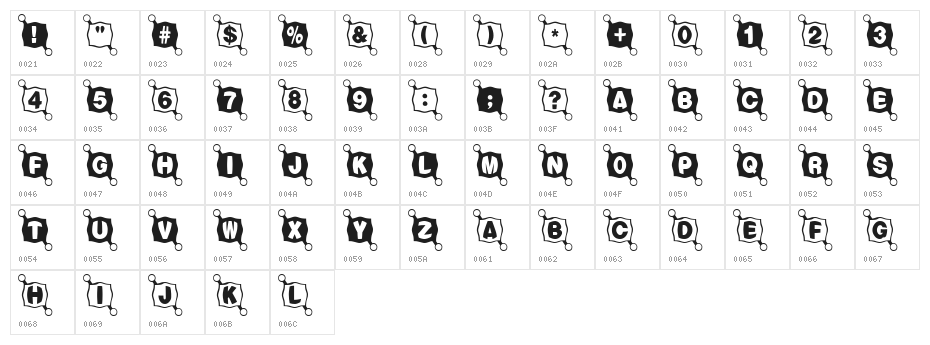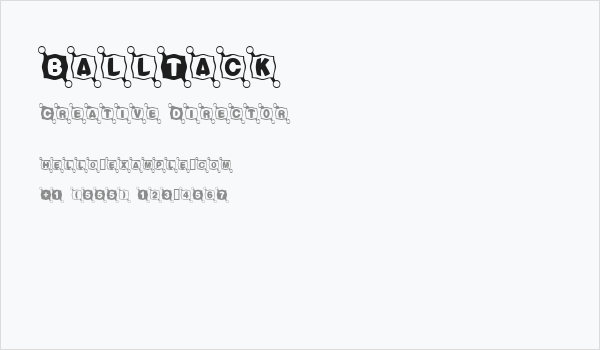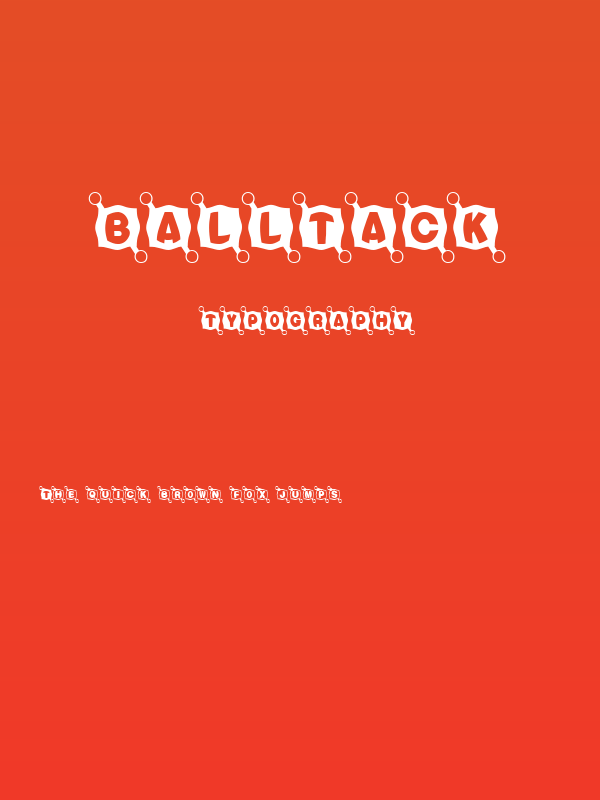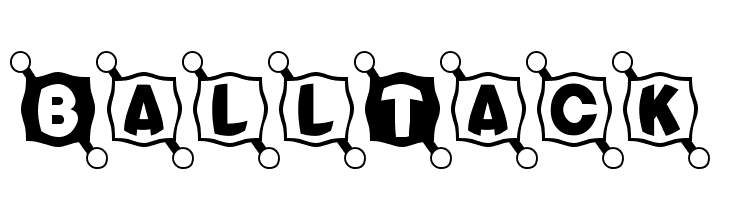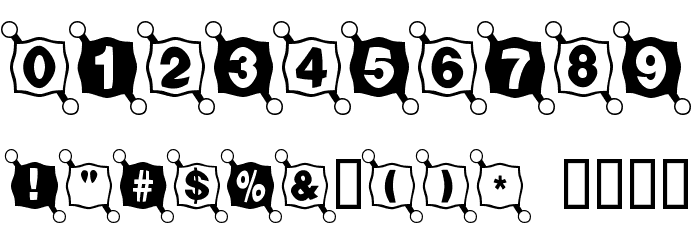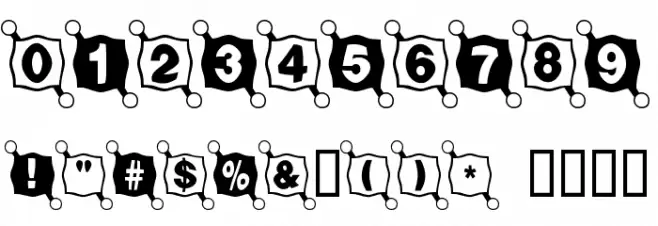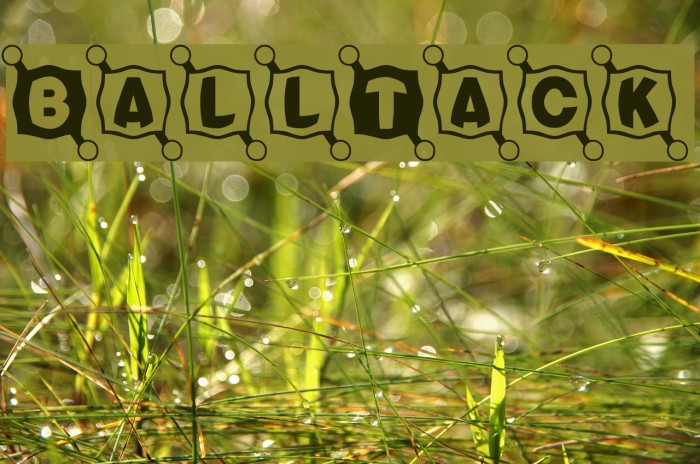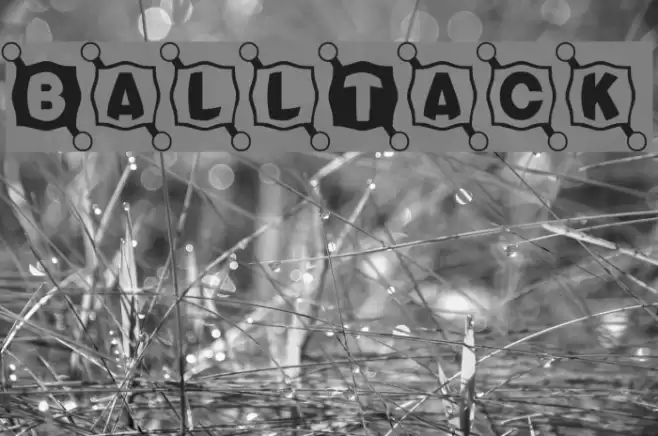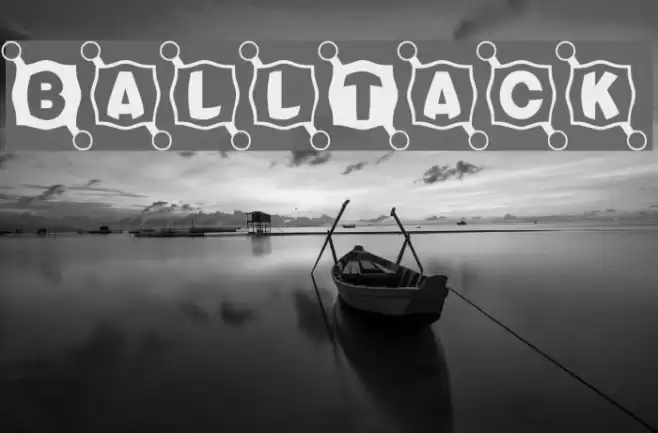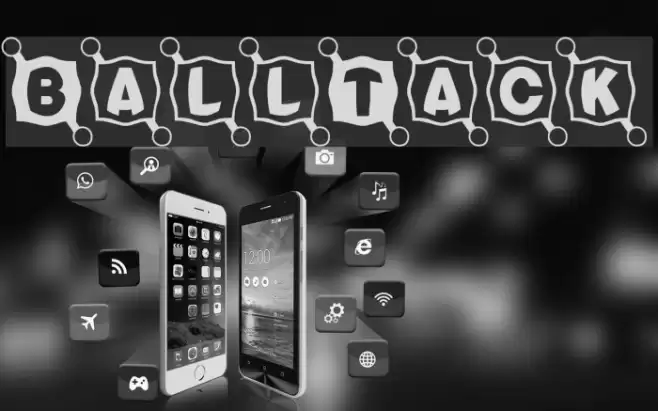
BallTack Font
✎ Decorative
BALLTACK अपरकेस
BALLTACK लोअरकेस
BALLTACK अन्य घर का काम
| श्रेणियाँ | Decorative |
| समग्र शैली | Playful, Whimsical |
| उपयोग का मामला | Headlines, Logos, Posters |
| सुझाए गए प्रोजेक्ट | Ideal for children's book covers, playful branding, party invitations, and creative posters. |